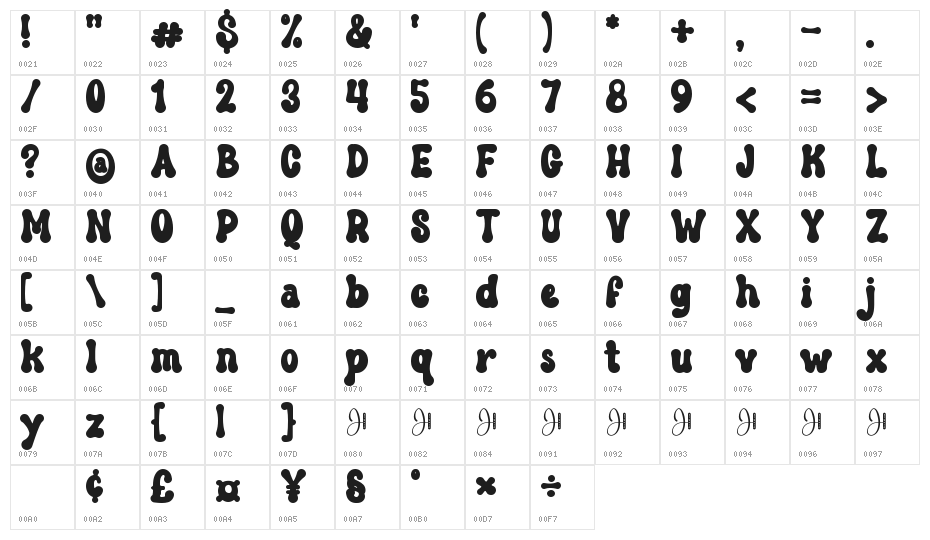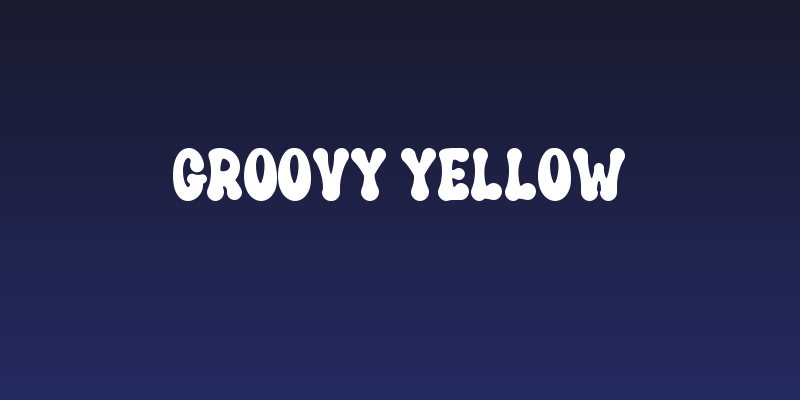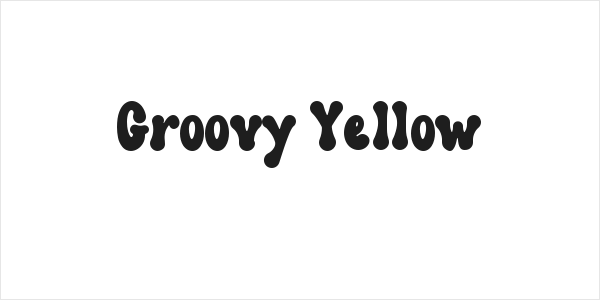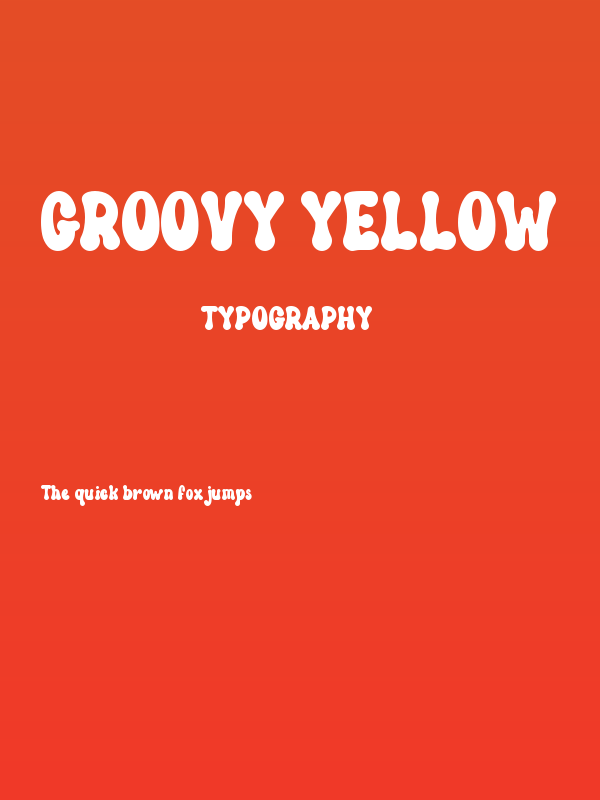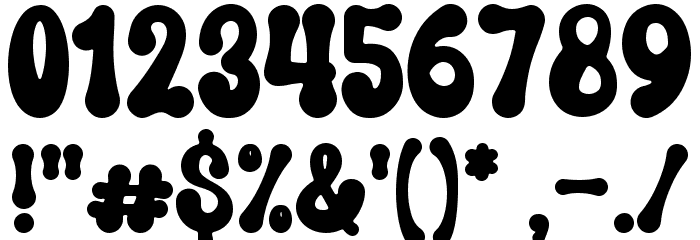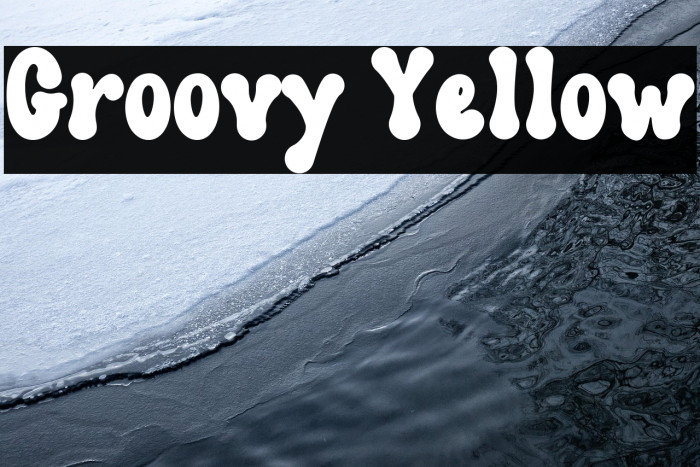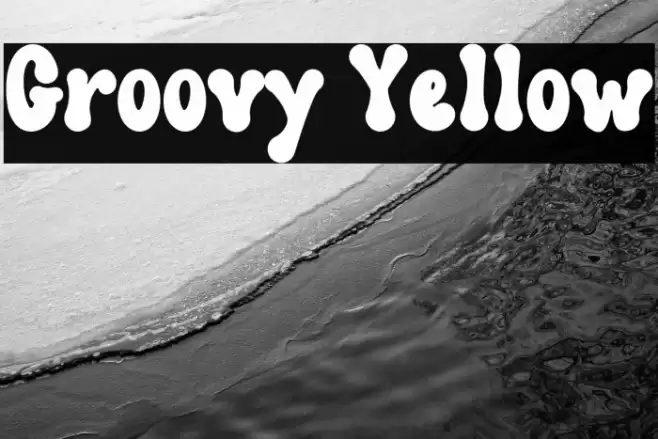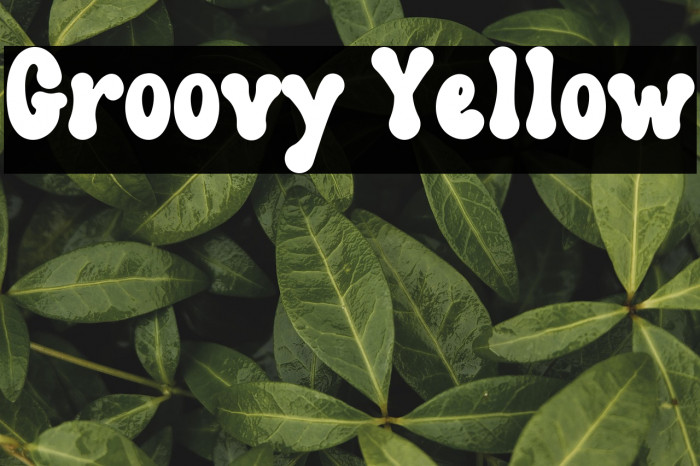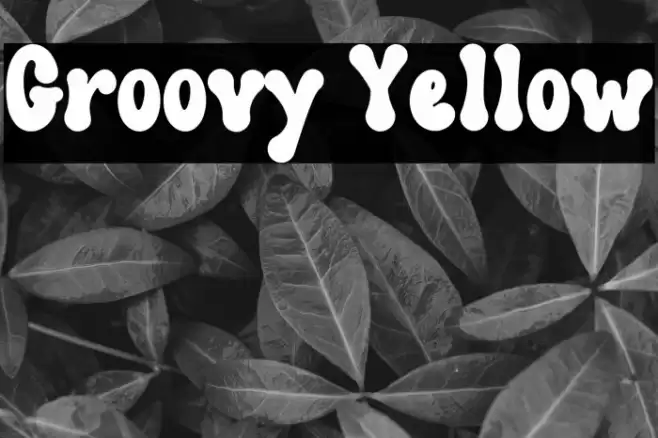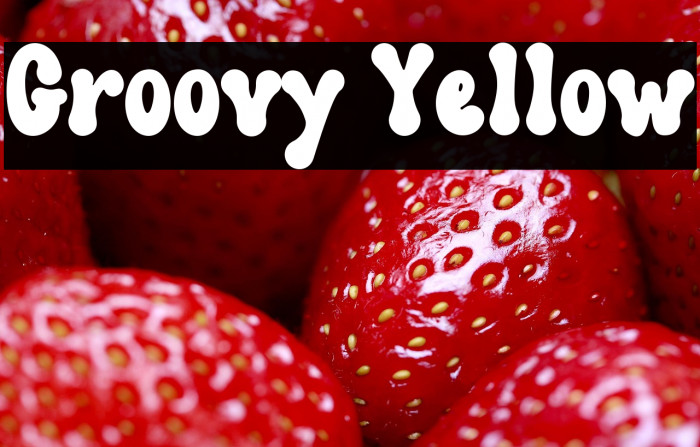
Groovy Yellow Font
| Gesamtstil | Vintage |
| Vorgeschlagene Projekte | Perfect for vintage-themed posters, album covers, branding for creative businesses, and playful merchandise designs. |